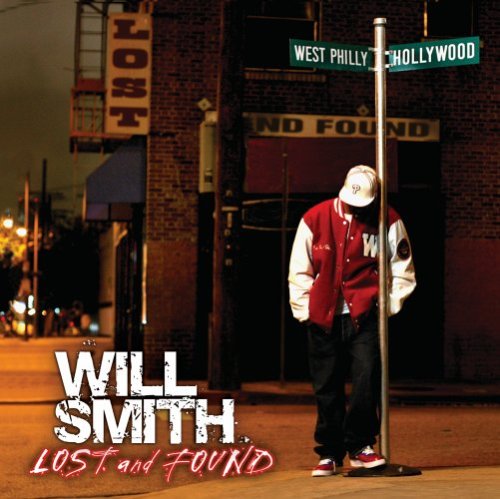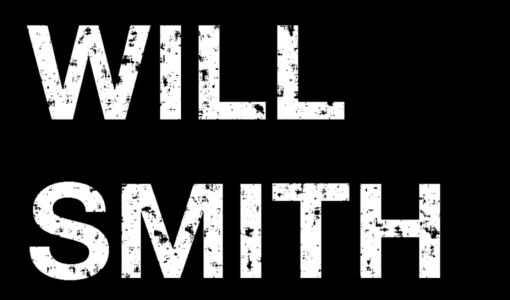
"Kaputter" Font gesucht
Ich bin schon lange am suchen nach einer bestimmten Fontart. Ich suche den, oder einen Font, der so aussieht wie bei Will Smith B0007QS4IC.01._SCLZZZZZZZ_.jpg
oder Survivor
"Highway to Heck" ist zumindest ähnlich.
Bei Will Smith handelt es sich nicht um einen fertigen Brokenfont, was man gut daran sieht, dass der Dreck bei den doppelt vorhandenen Ls und Is nicht an den selben Stellen sitzt. Da hat also nachher jemand einen Filter drübergeschickt (PhotoShop: Störungen hinzufügen o.ä.). Bei Survivors sieht das schon anders aus, da gibt es gemeinsame Störungen, die nachträglich noch verstärkt wurden.
Von diesen »distorted« Schriftarten gibt es zahllose kostenlose im Netz, ansonsten kannst erst den Text setzen und dann selbst einen Filter drüberlegen.
Danke für Eure schnellen Antworten. Ja Highway to Heck sieht so ähnlich aus, aber ich brauche das fast identisch. Gibts da einen bestimmten Namen wie der Font heißt?
@ Psocopterus: Welchen Filter würdest du empfehlen?
Ich hab mal ein bisschen mit dem "Kunstfilter, Schwamm" gespielt, anschließend den Kontrast verstärkt ein bisschen Weichzeichner, dann wieder stark scharfzeichnen, sieht etwa so aus:
Ach ja, das ist die Neue Helvetica 75 bold.
Meine Vorredner haben – natürlich – in allen Punkten Recht, wiewohl mich die »Zerstörungen« beim Versal-S an die – in diesem Sektor wohl populärste Schrift – Base 02 von Clement Nicolle (stereotype.net) denken lässt.